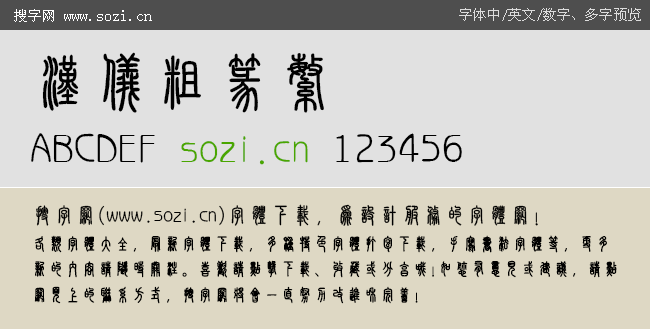
漢儀粗篆繁
搜字網(wǎng)給大家提供一款中文字體下載,漢儀粗篆繁是篆字,大篆指甲骨文、金文、籀文、六國(guó)文字。篆體是主要在秦朝和秦朝之前使用的字體,它們保存著古代象形文字的明顯特點(diǎn)。特點(diǎn)是形體勻逼齊整、字體較籀文容易書寫。漢儀公司根據(jù)這種字體特點(diǎn)忠實(shí)還原了這種字體風(fēng)格。
• 風(fēng)格類別: 篆書